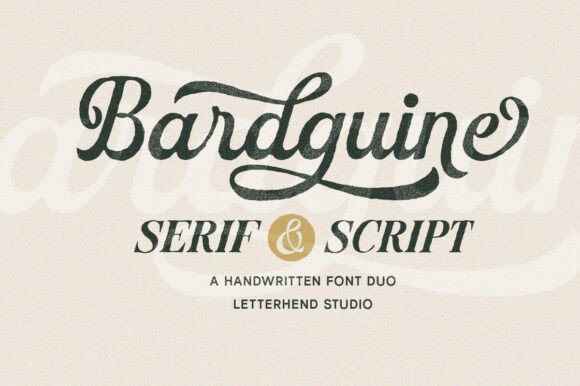
Bardguine Serif & Script Duo Font
Mencari elemen reka bentuk yang sesuai boleh menjadi mencabar, tetapi Bardguine Serif & Script Duo Font menawarkan koleksi luar biasa yang menaik taraf karya anda serta-merta.
Sama ada anda mencipta produk POD (Print on Demand), jemputan perkahwinan atau grafik media sosial, Bardguine Serif & Script Duo Font amat bersesuaian.